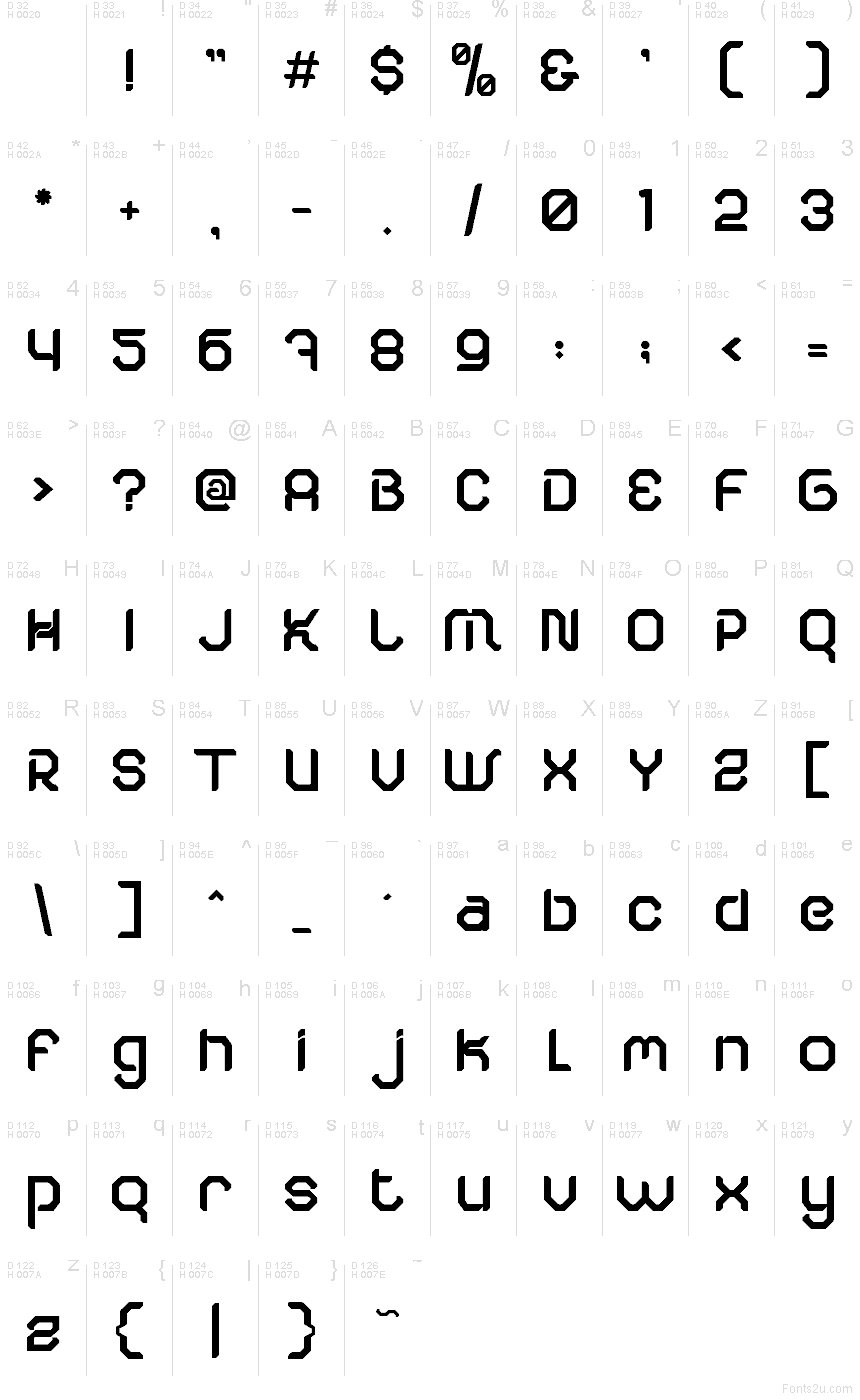
Snapshock
Snapshock od Putracetol Studio je futuristické bezplatné písmo typu display, definované orezanými rohmi, ostrými diagonálnymi rezmi a modulárnou siluetou, ktorá pripomína značenie alebo herné rozhrania. Opakujúce sa fazety zaisťujú vizuálnu súdržnosť, zatiaľ čo občasné dlhé ťahy a otvorené vnútorné priestory bránia tomu, aby dizajn pôsobil ako obyčajný geometrický blok.
Táto kombinácia uhlového rytmu a kompaktnej hmoty sa skvele hodí pre branding esportu, sci-fi plagáty, grafiku streamov, obaly albumov alebo titulky technologických akcií. Najlepšie vynikne v krátkych nadpisoch, kde tieto fazetové tvary pomáhajú orámovať layout a dodať logám, obalom alebo reklamným bannerom ostrejší digitálny nádych.